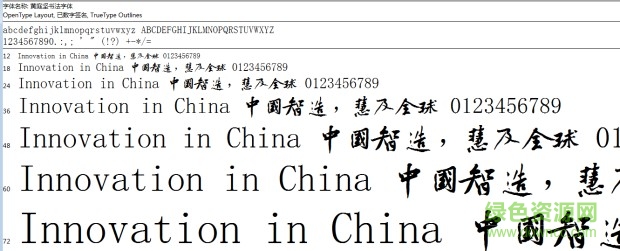
黃庭堅(jiān)書法字體是一款非常時(shí)尚的字體,這款字體字形行云流水,飄逸優(yōu)美,各種場合都很適用哦,感興趣的朋友趕緊來綠色資源網(wǎng)下載吧!
黃庭堅(jiān)的書法特點(diǎn):可分兩個(gè)階段。前一階段即他自稱的元佑間書。是繼承各家,融化為己。后一階段,則極力創(chuàng)新。他對(duì)自己要求很高很嚴(yán)格,常否定元佑間即四十九歲前所寫的作品。說:“元佑間書,筆意癡鈍,用筆多不到?!鄙踔猎诒毁H戎州時(shí)說:“見舊書多可憎;大概十字中有三四字差可耳。
早年結(jié)體上內(nèi)緊外松縱橫逸出點(diǎn)畫起伏跌宕,汪洋恣肆,字體開張充滿意適,筆法瘦勁。黃庭堅(jiān)書法的結(jié)體是從顏真卿處得來,中宮收緊,由中心向外輻射狀,縱伸橫逸,如蕩槳,如撐舟,氣魄宏大,器宇軒昂,其個(gè)性十分顯著,黃庭堅(jiān)結(jié)合他們各自特點(diǎn)吸收,便獨(dú)創(chuàng)一體——黃體。
晚年所做行書酌每個(gè)字,在結(jié)枸布局上,都是中宮緊密,而筆畫從中間向四外放射,無論筆畫長短都接于字中間的圓心。這種輻射式的結(jié)構(gòu),字心緊密穩(wěn)實(shí),向外拓展的筆畫又顯得瀟灑不拘。漢字結(jié)構(gòu)本身具有多樣性,用這種處理方法,將其排列在一起,造成一種顧盼生姿。渾融瀟灑的效果。運(yùn)筆從容徐迂,略帶生澀,結(jié)構(gòu)略成“欹側(cè)”之勢,滿篇文字都好像在翩翩起舞,給人一種別開生面的愉悅之感。